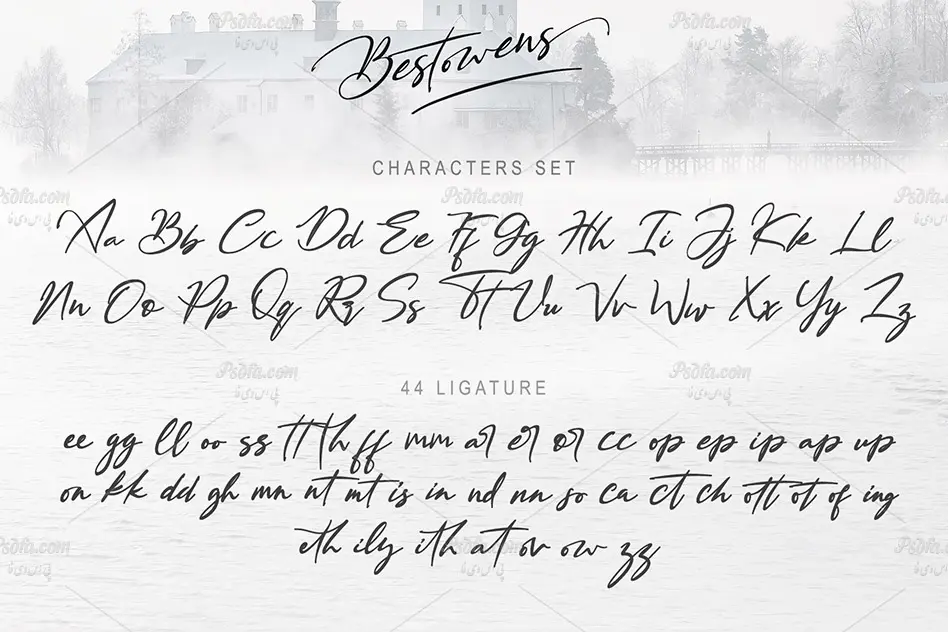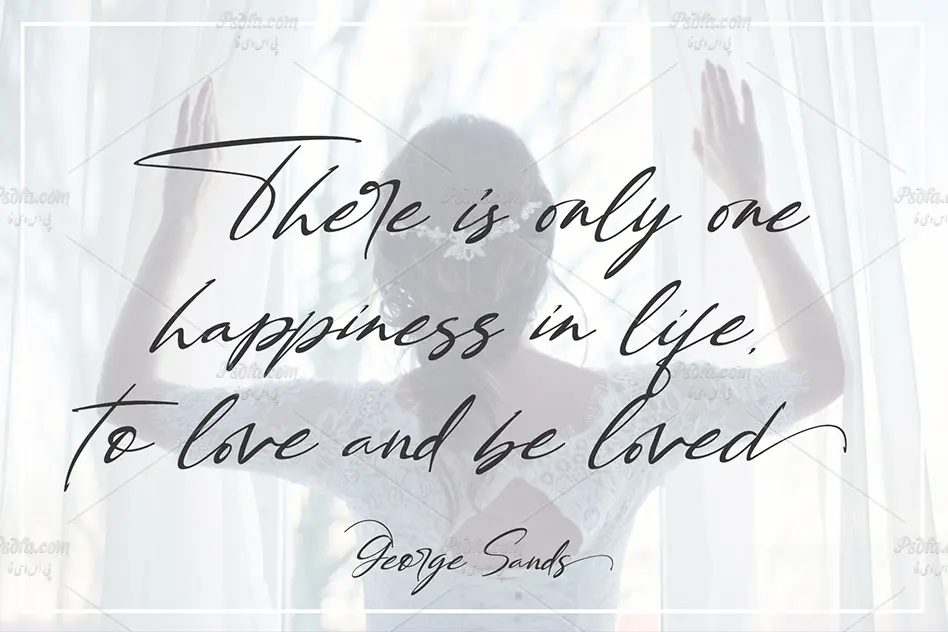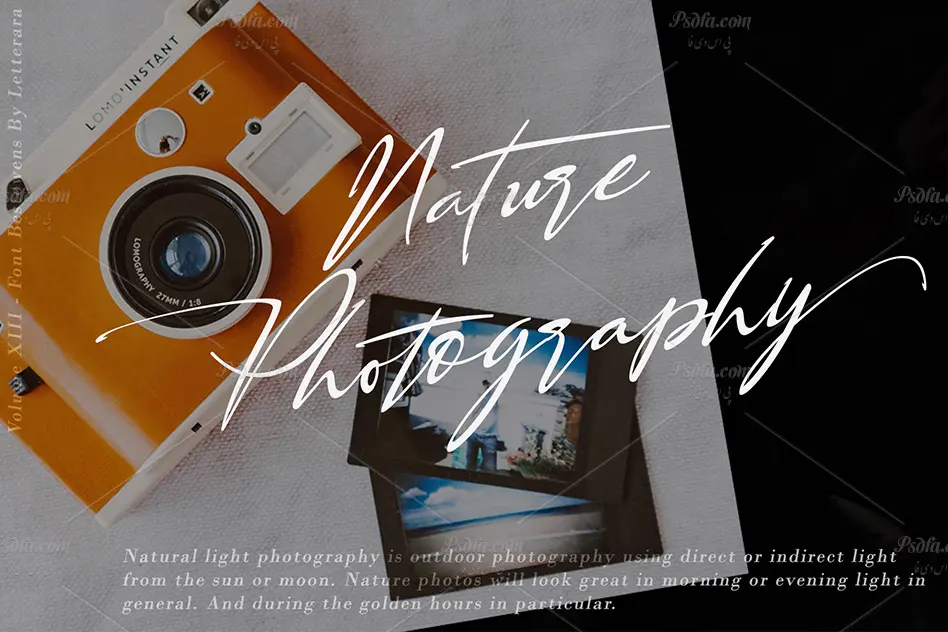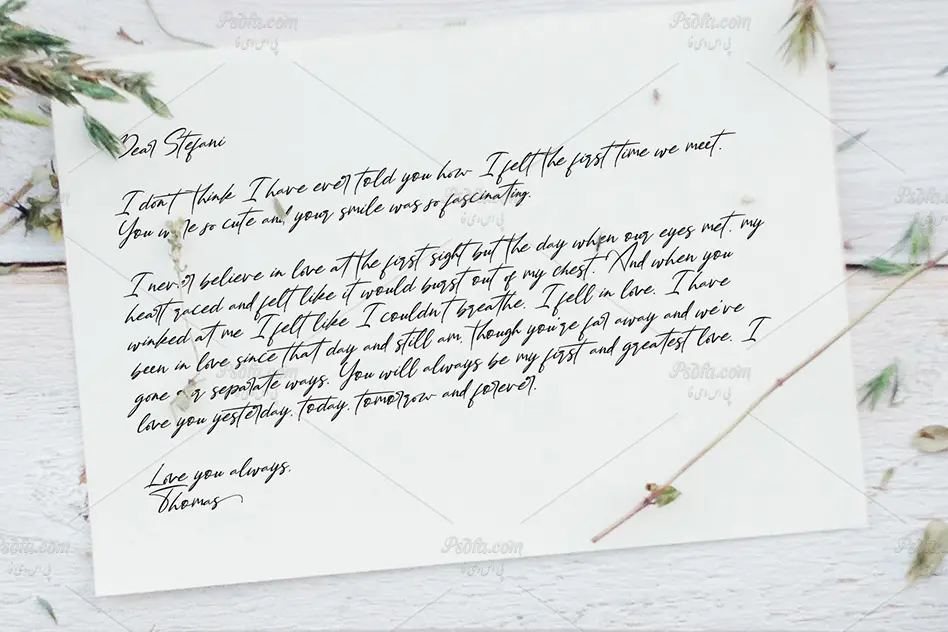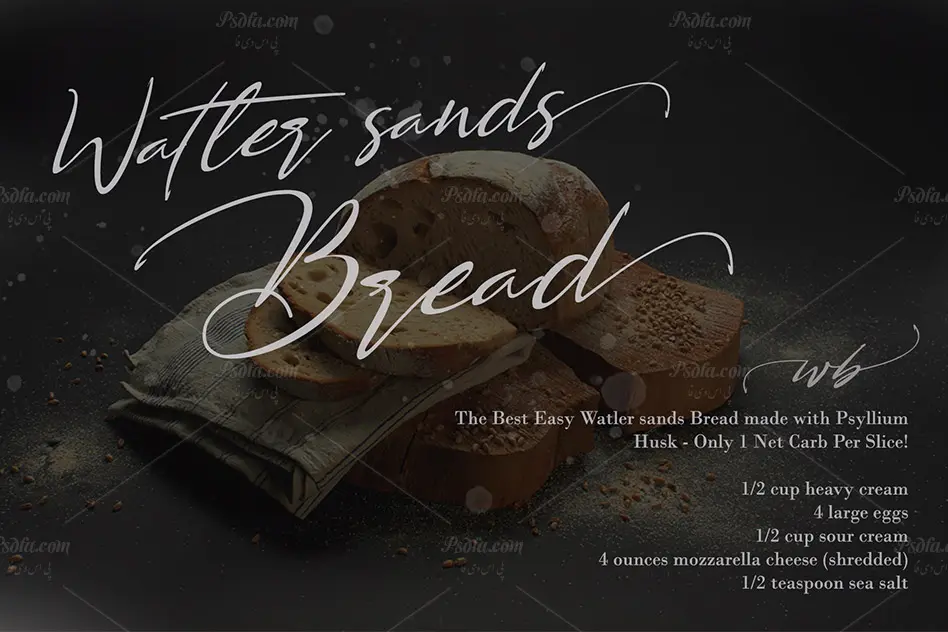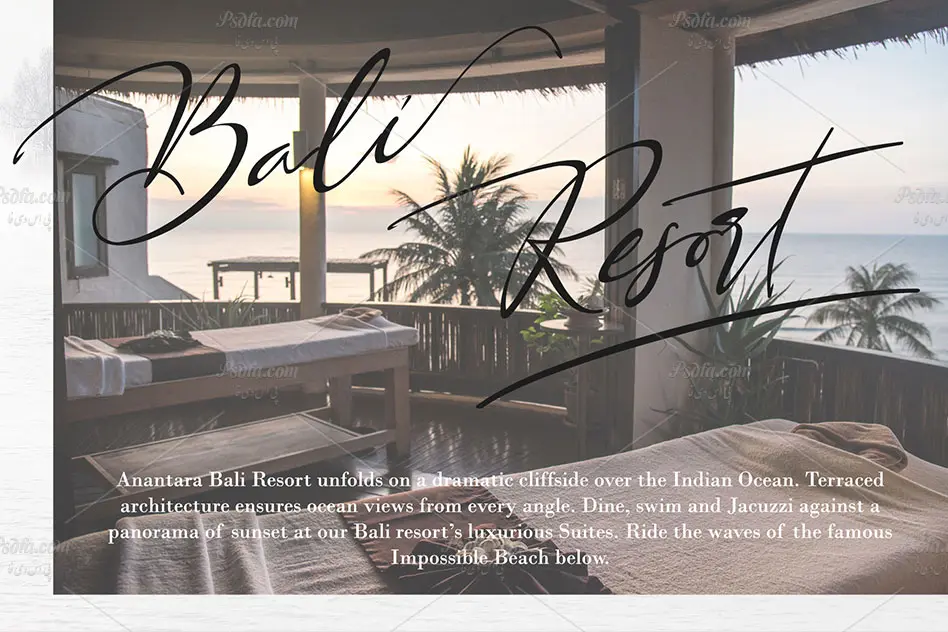
فونت دستنویس انگلیسی Bestowens مناسب برای طراحی انواع کارت و پوستر
فونت دستنویس انگلیسی Bestowens
در این مطلب شاهد فونت دستنویس انگلیسی Bestowens مناسب جهت استفاده در طراحی انواع کارت و پوستر می باشید. این فونت زیبا در قالب 10 فایل otf بر روی سایت قرار گرفته است که با نصب این مجموعه فایل در پوشه فونت های سیستم خود قادر به استفاده از آن ها در تمام نرم افزارهای گرافیکی و ویرایشگر متن از جمله نرم افزار فتوشاپ ، افترافکت ، پریمیر ، مجموعه نرم افزاری آفیس و … خواهید بود. فونت Bestowens در وزن های مختلف معمولی (Regular) ، ضخیم (Bold) ، مورب (Italic) ، سبک (Light) ، باریک (Thin) ، شکسته (Semi) و نسخه ضخیم وزن های ذکر شده طراحی شده است که می توان از آن ها در طراحی و گرافیک همچون طراحی انواع کارت تبریک ، کارت پستال ، کارت عروسی ، طراحی پوستر ، کارت ویزیت ، طراحی صفحات وب و … استفاده نمود.